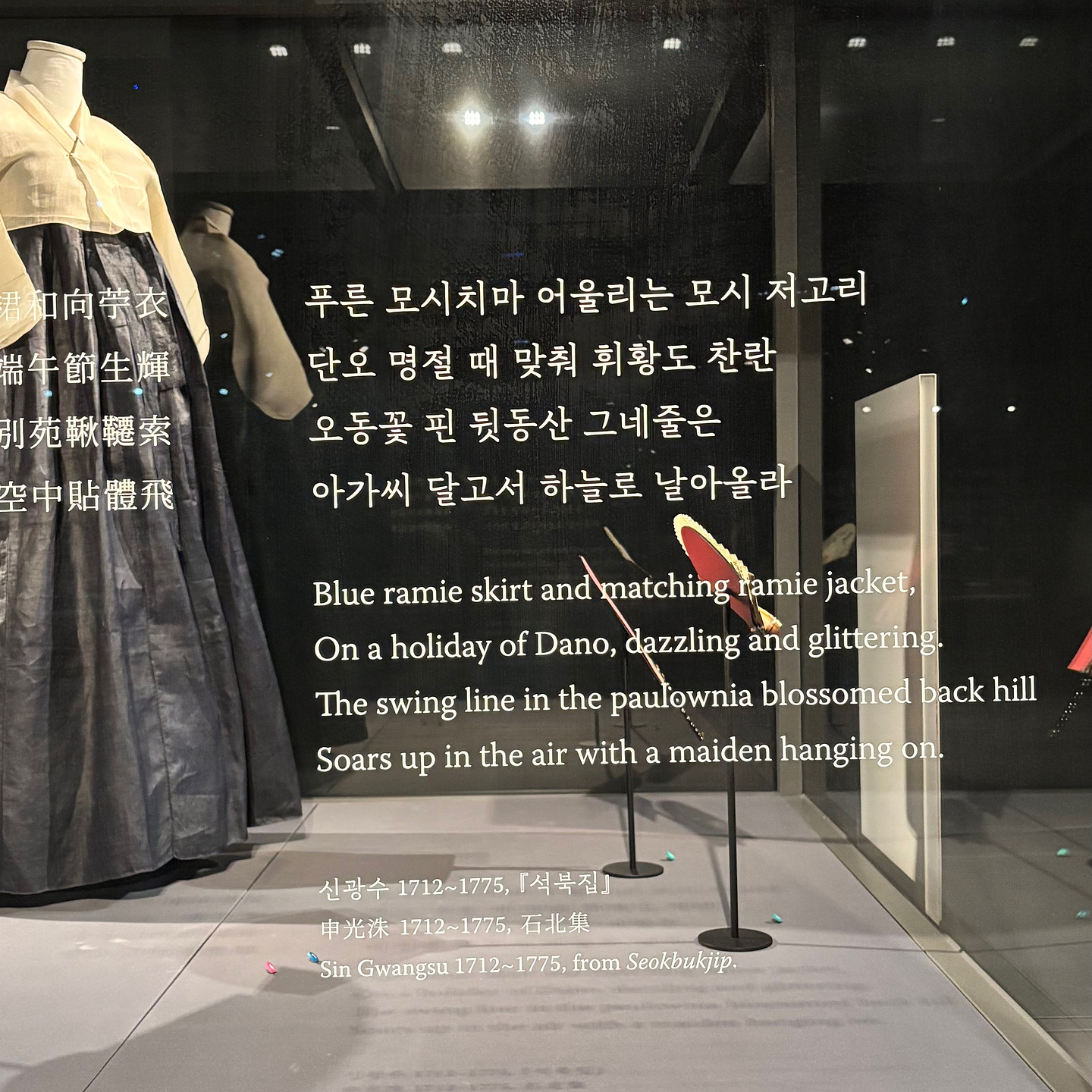
SD정체
SD정체 830 같습니다 다만 형태는 같은데 두께감에 좀 차이가 있어 전시 하신 분이 프로그램으로 폰트를 두껍게 하셨거나 아니면 프린트 시 두껍게 출력된 것 같습니다(유료 폰트라 정확히 모르겠습니다) https://www.sandollcloud.com/font/283/Sandoll-Jeongche